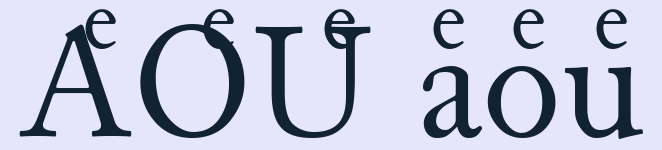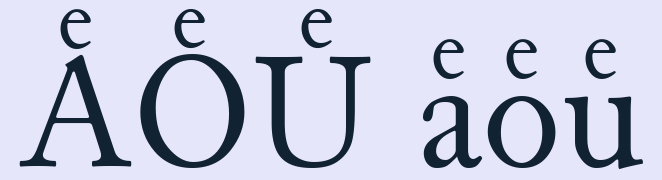
Schrift mit »e« als Ersatz für Umlautpunkte
Ich bitte um Hilfe. Gesucht wird eine lateinische Schrift, wahrscheinlich eine Renaissance-Antiqua, als einsetzbarer Font, bei dem die Umlautpunkte durch auf die Vokale gestellte »e« oder »E« ersetzt wurden. Wie es vor den Umlautpunkten gemacht wurde. Aber nicht als gebrochene Schrift, sondern lateinische Typen mit Serifen.
Na wenn du das selbst nicht weißt, woher sollen wir’s dann wissen?! :shock:
Aber im Ernst, schreib doch bitte gleich dazu, in welche Version(en) der Andron diese Umlaute haben und wie sie erzeugt werden!
In der Junicode lassen sich gesuchten Varianten entweder per combining letter small e oder per PUA-Unicode erzeugen – also leider nur durch eine Veränderung des Texts an sich statt einfach per Opentype-Schalter.
Die PUA-Unicodes wären \ue02c\ue244\ue32b \ue42c\ue644\ue72b
(Die Vorschausoftware stellt die kombinierten Zeichen leider nicht richtig dar. Mit professioneller Satzsoftware ist das aber kein Problem.)
Und in der Cardo funktioniert es ganz genauso: entweder per PUA oder kombinierendem kleinem e.
In Andron Mega und in der bei MUFI erhältlichen (freien) Andron funktioniert es genauso.